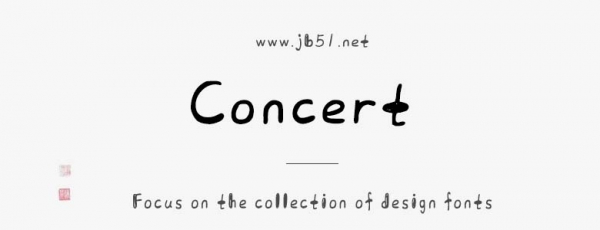
Concert英文卡通手寫(xiě)字體,筆觸略適中,字形優(yōu)美,具有很好的視覺(jué)感,適合應(yīng)用于藝術(shù)設(shè)計(jì)、平面宣傳設(shè)計(jì)、網(wǎng)頁(yè)設(shè)計(jì),書(shū)法字帖等領(lǐng)域。有需要的朋友快來(lái)本站下載使用吧。